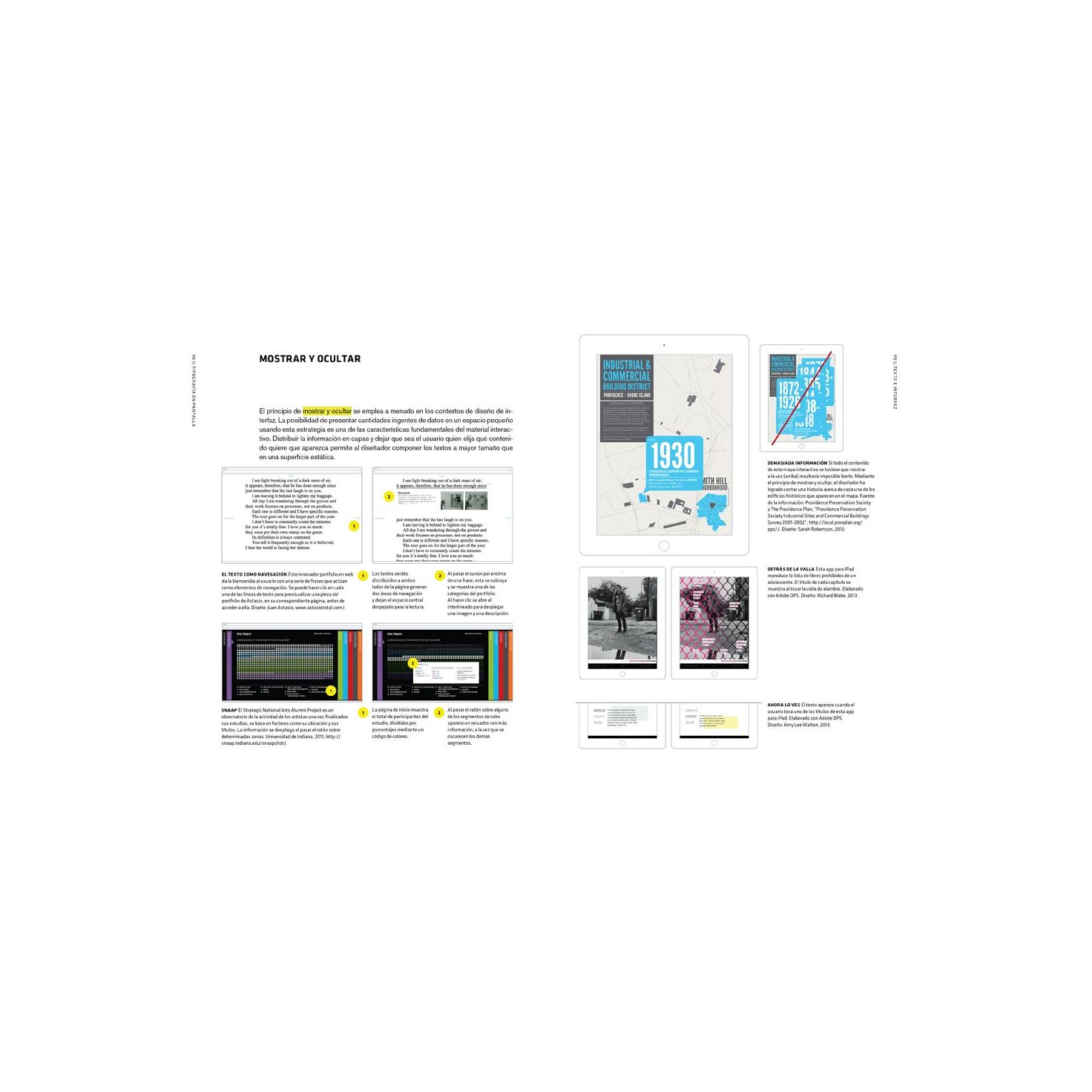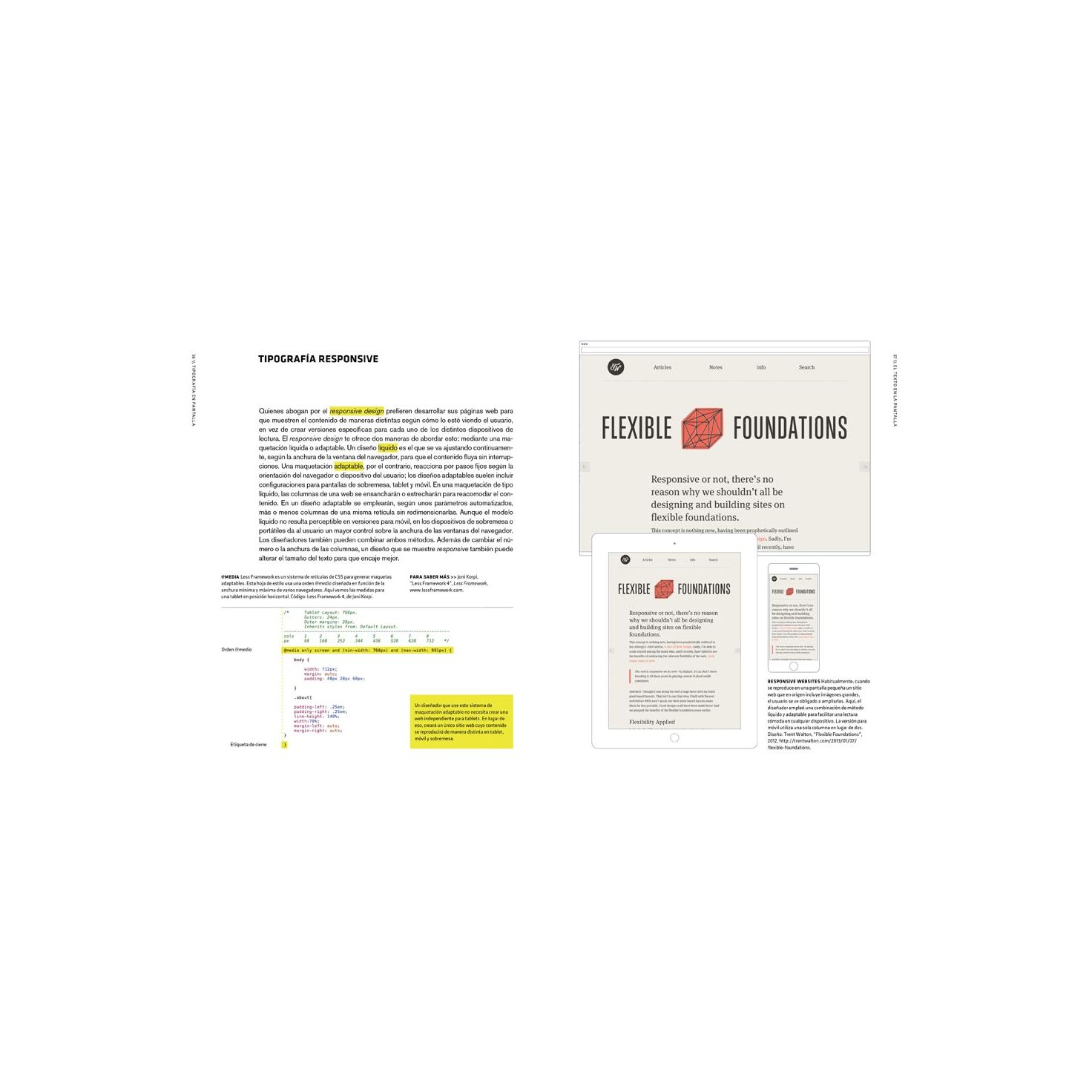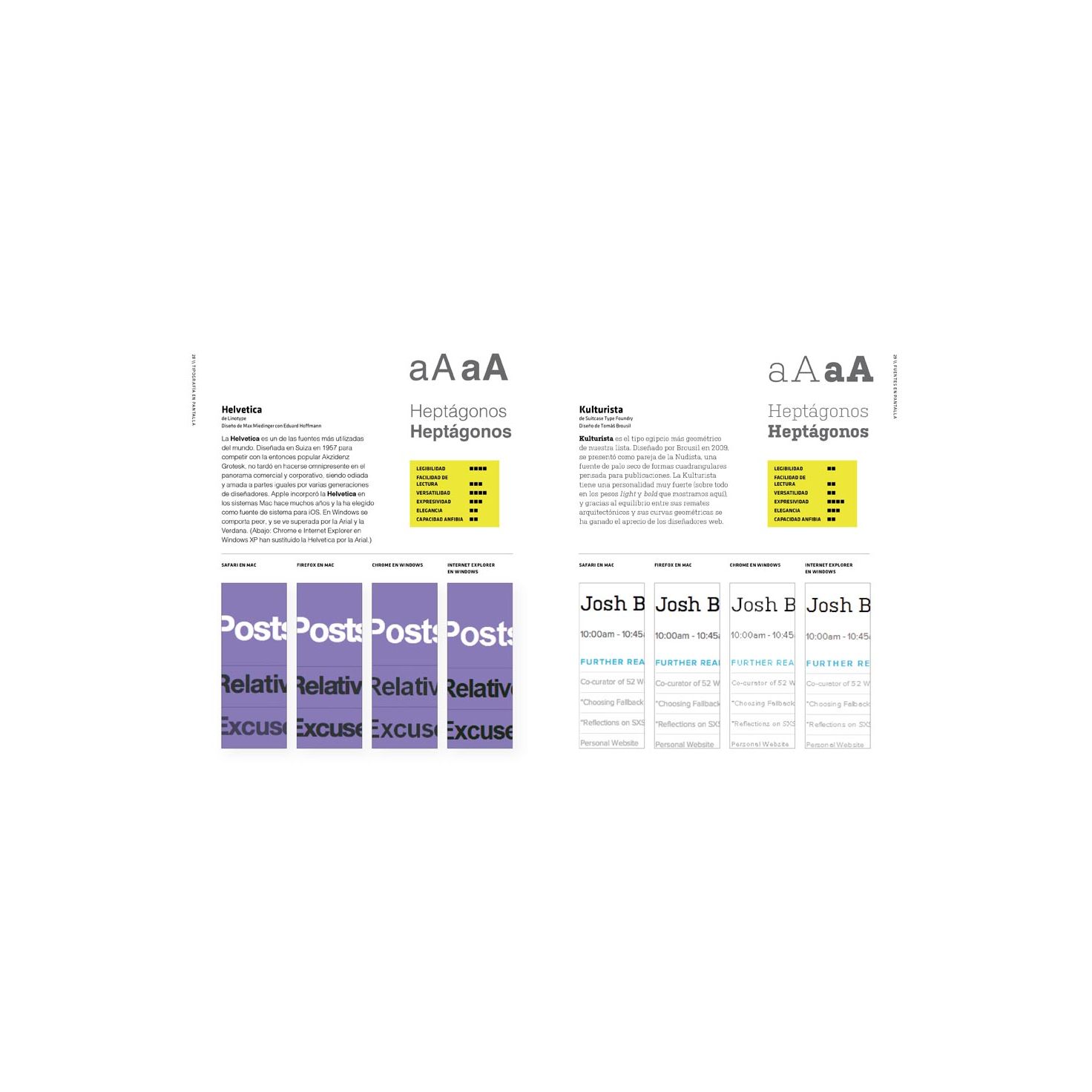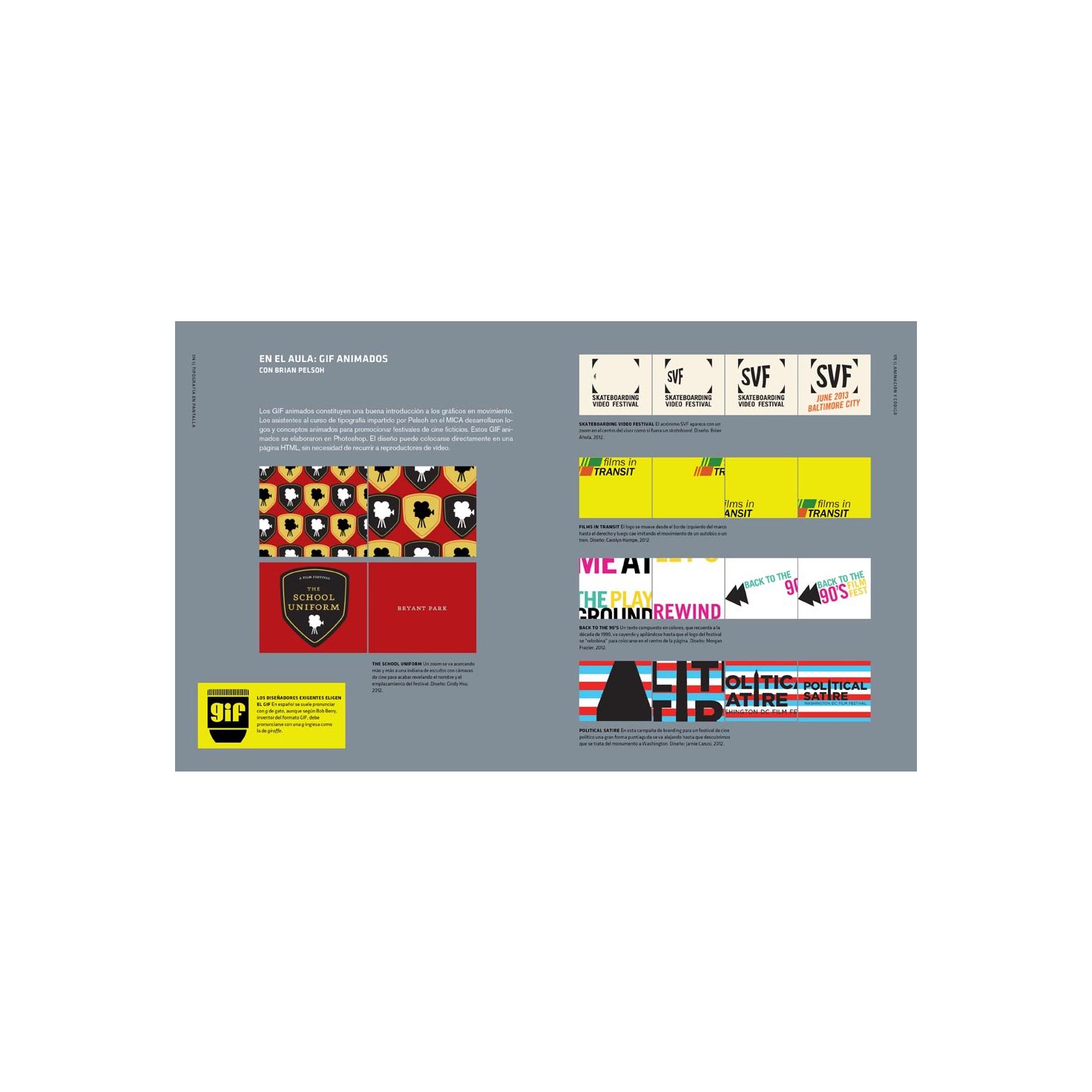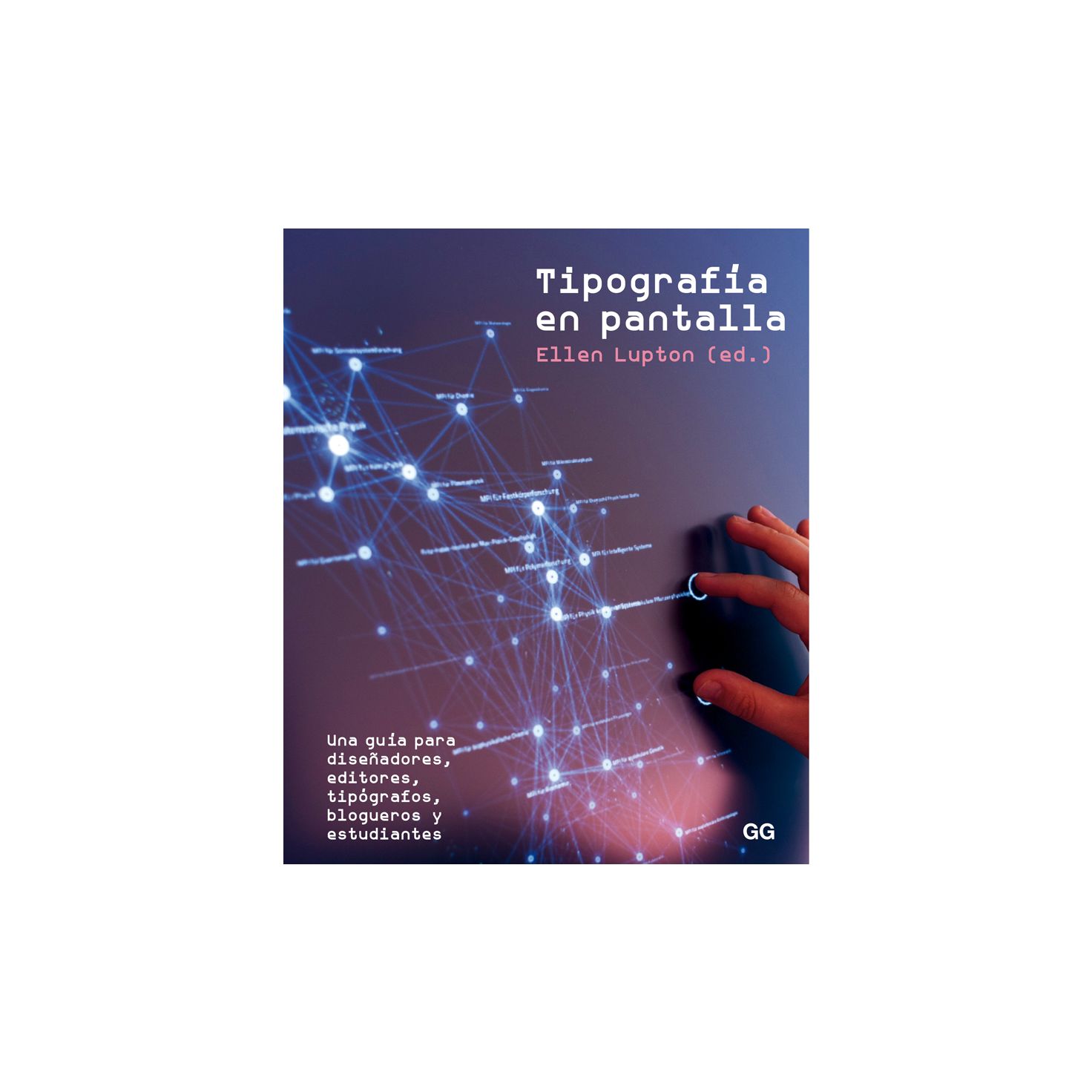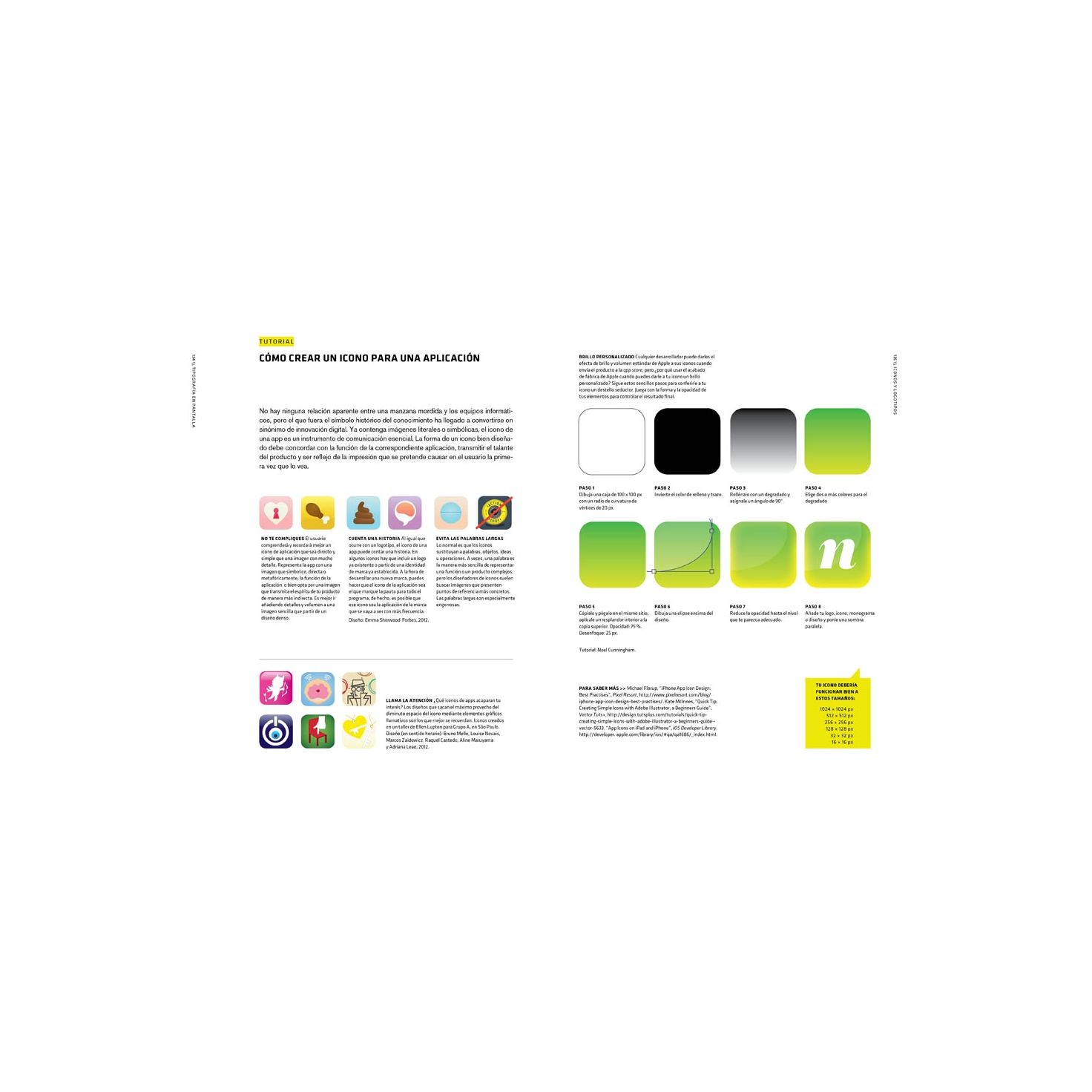
Tipografía en pantalla
La tipografía es una disciplina histórica que cuenta con abundantes y rigurosas normas para su correcto ejercicio. Pero cuando la tipografía se desembaraza de su condición estática y se hace virtual, los lectores alteran los parámetros de la representación visual según nuevas necesidades y preferencias. ¿Qué ocurre entonces? ¿Cómo puede el diseñador controlar esos principios y garantizar la calidad tipográfica de sus composiciones?
Escrito por un equipo de diseñadores, docentes y estudiantes del MICA y editado por Ellen Lupton, Tipografía en pantalla no solo aborda los nuevos fundamentos de la tipografía cuando se usa en pantalla sino que explora en profundidad los entresijos del diseño destinado a este soporte. Para ello se centra en las cuestiones concretas que surgen en el día a día del desarrollo de un proyecto de diseño digital: desde el amplio catálogo de fuentes existentes para web hasta cómo componer los párrafos y alinear el texto en pantalla o cómo tratar la señalética y crear sistemas de iconos para un entorno digital. Lejos de ignorar el saber acumulado por años de desarrollo y evolución de la tradición tipográfica, la guía se sube a hombros de esta disciplina histórica para seguir avanzando y forjando nuevos recursos técnicos y nuevas formas visuales.
Tipografía en pantalla es un libro no solo dirigido a los profesionales y estudiantes de diseño sino también al desarrollador, que en estas páginas conocerá mejor los principios visuales del diseño, y al editor o redactor de contenidos, que obtendrá un control más sofisticado de las herramientas y los sistemas digitales.